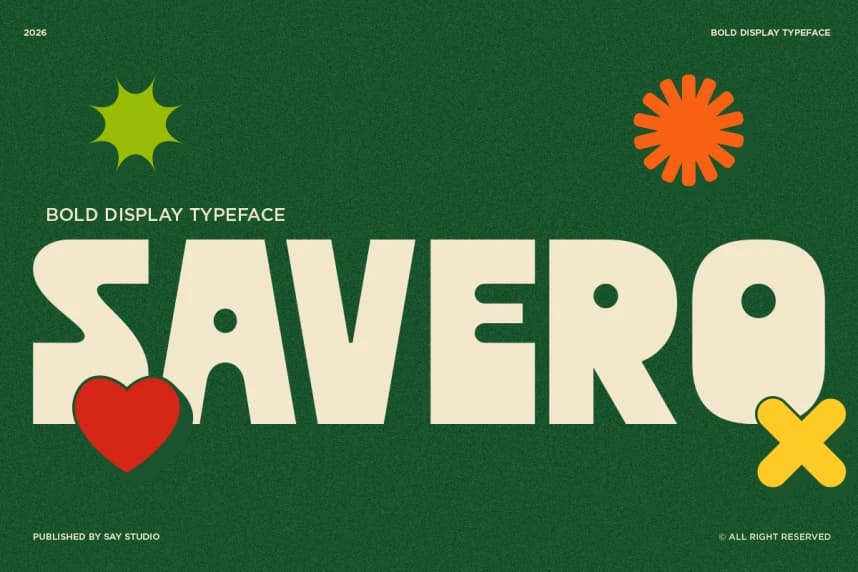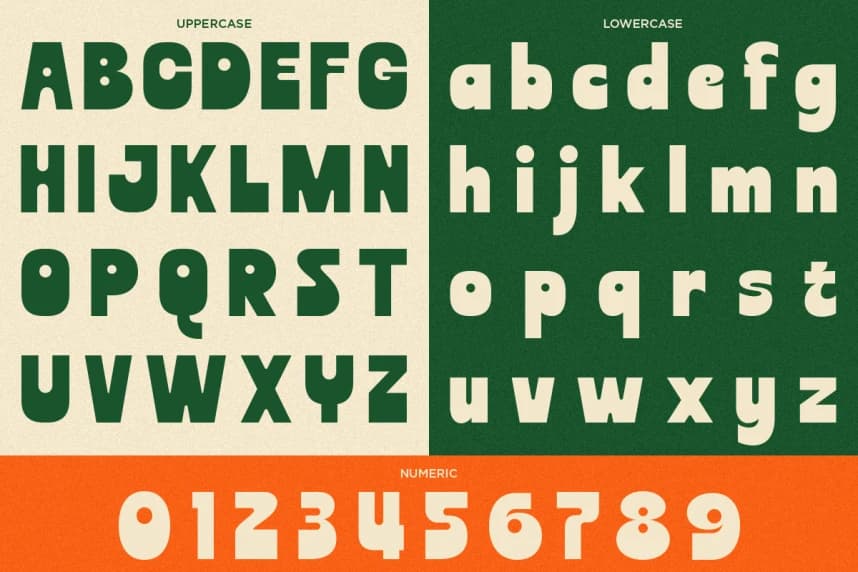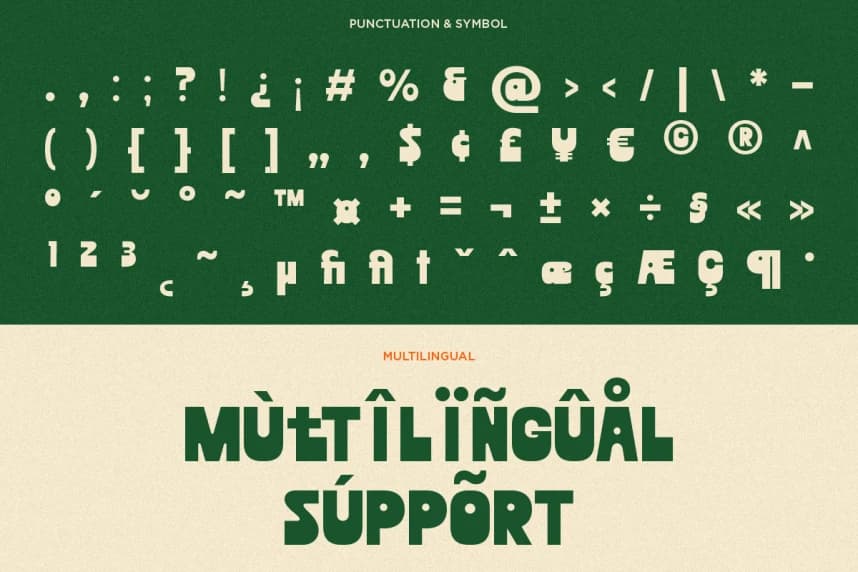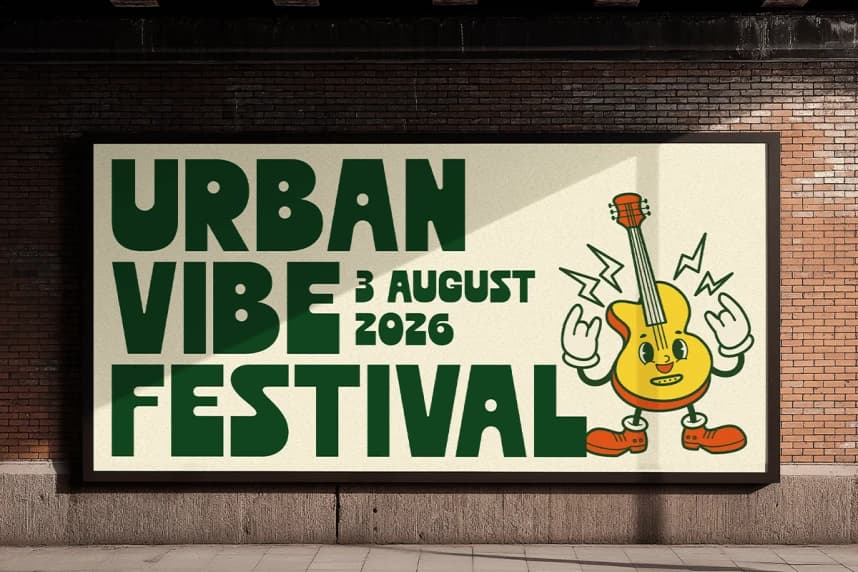
Savero Font
Savero Font, modern tipografiye oyunlu ve enerjik bir kişilik kazandıran kalın bir gösteri tipi yazı karakteridir. Güçlü, iri hatlı harf biçimleri ve yumuşak, yuvarlatılmış kenarlarıyla tasarlanmış olan bu yazı, güçlü bir görsel varlık sunarken aynı zamanda dostane ve erişilebilir bir hava da korur.
Savero Font, modern tipografide oyunlu ve enerjik bir kişiliğe sahip olan kalın bir gösteri yazı tipidir. Güçlü, kalın harf biçimlerine ve yumuşak yuvarlatılmış uçlara sahip olan bu yazı tipi, güçlü bir görsel etki sunarken dostça ve ulaşılabilir bir hava da korur.